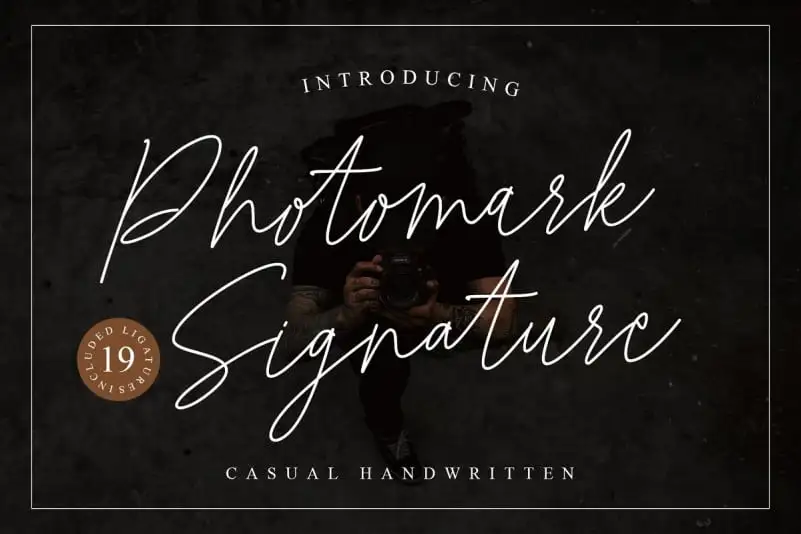
Photomark Signature Font – Download Grátis
A Photomark Signature Font é uma excelente escolha para quem busca estilo único e autêntico em seu design gráfico. Criada pelo designer vanpatelona, esta fonte script monolínea possui um charme casual que transmite uma sensação verdadeiramente única tanto nos caracteres maiúsculos quanto nos minúsculos. Esta fonte é perfeita para diversas aplicações como branding, assinaturas de documentos, design de cartões de convite, criação de fotomark, desenvolvimento de logotipos e outros projetos gráficos. Com seu estilo único em letras maiúsculas e minúsculas, a Photomark Signature Font oferece um elemento distintivo que pode deixar seu projeto ainda mais especial. Não perca tempo, explore e personalize suas próximas criações com esta fonte incrível!